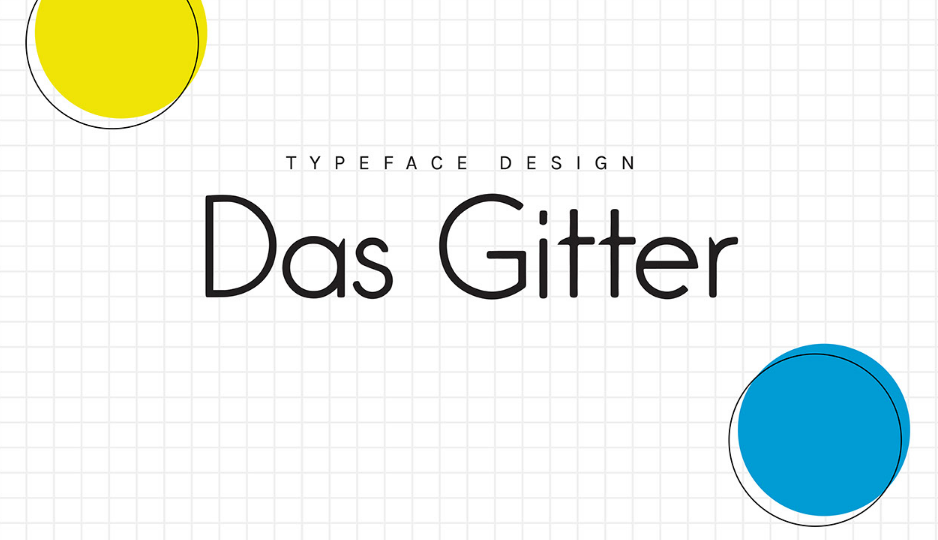
Das Gitter Typeface – Download Grátis
Introduzimos para você a Das Gitter Typeface, uma nova adição à família de tipos que se destacará por sua simplicidade e modernidade. Desenhada pelo talentoso designer Cinthya Noviana, esta tipografia inova ao misturar elementos do estilo suíço com um toque geométrico, criando um design minimalista e elegante. Das Gitter foi projetado para ser uma escolha ideal para qualquer aplicação que valoriza a simplicidade moderna, seja em materiais impressos ou digitais. Com sua estrutura retangular e linhas leves, esta fonte irá destacar seu texto de maneira clara e precisa. Uma opção perfeita para quem busca um tipo que não apenas ressalta nas telas digitais, mas também transmite seriedade e modernidade em suas publicações impressas. Instale a Das Gitter Typeface na sua próxima criação e deixe marcar a diferença com esse novo design único.